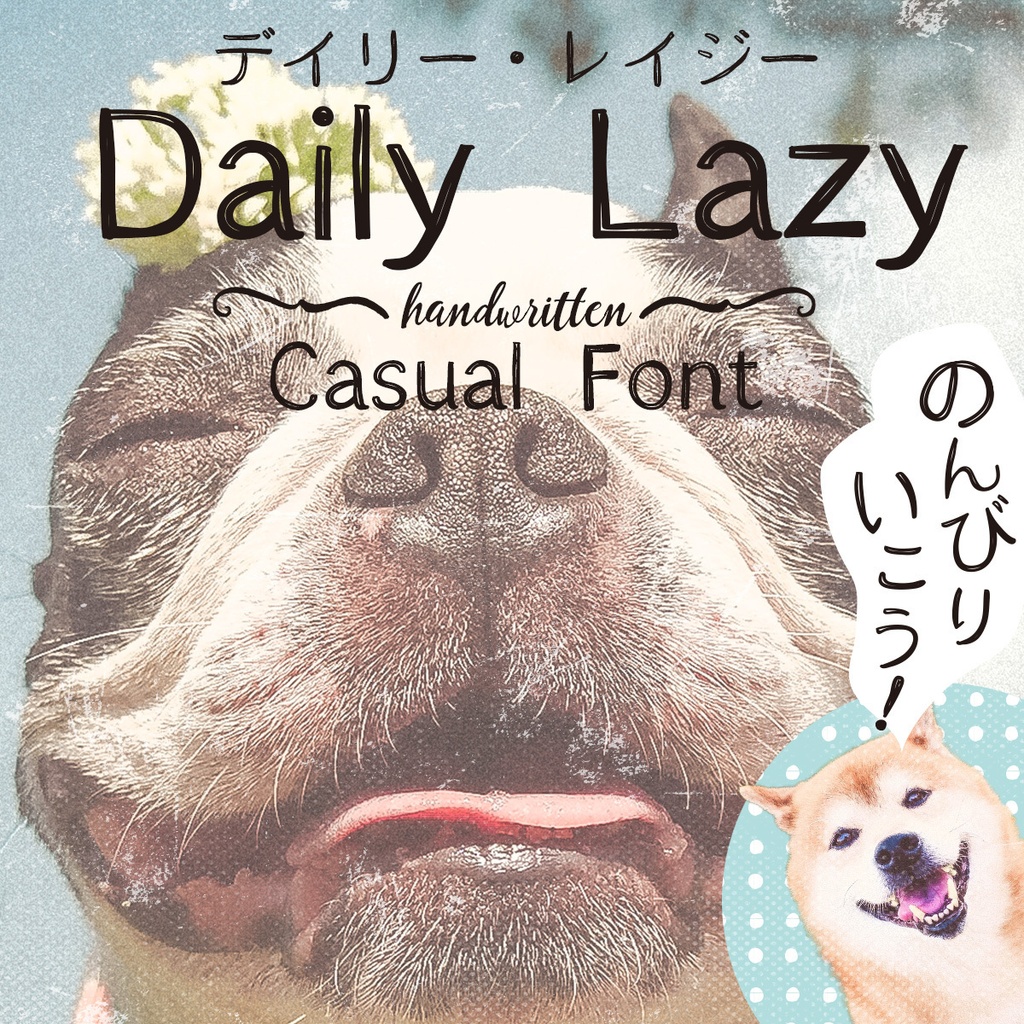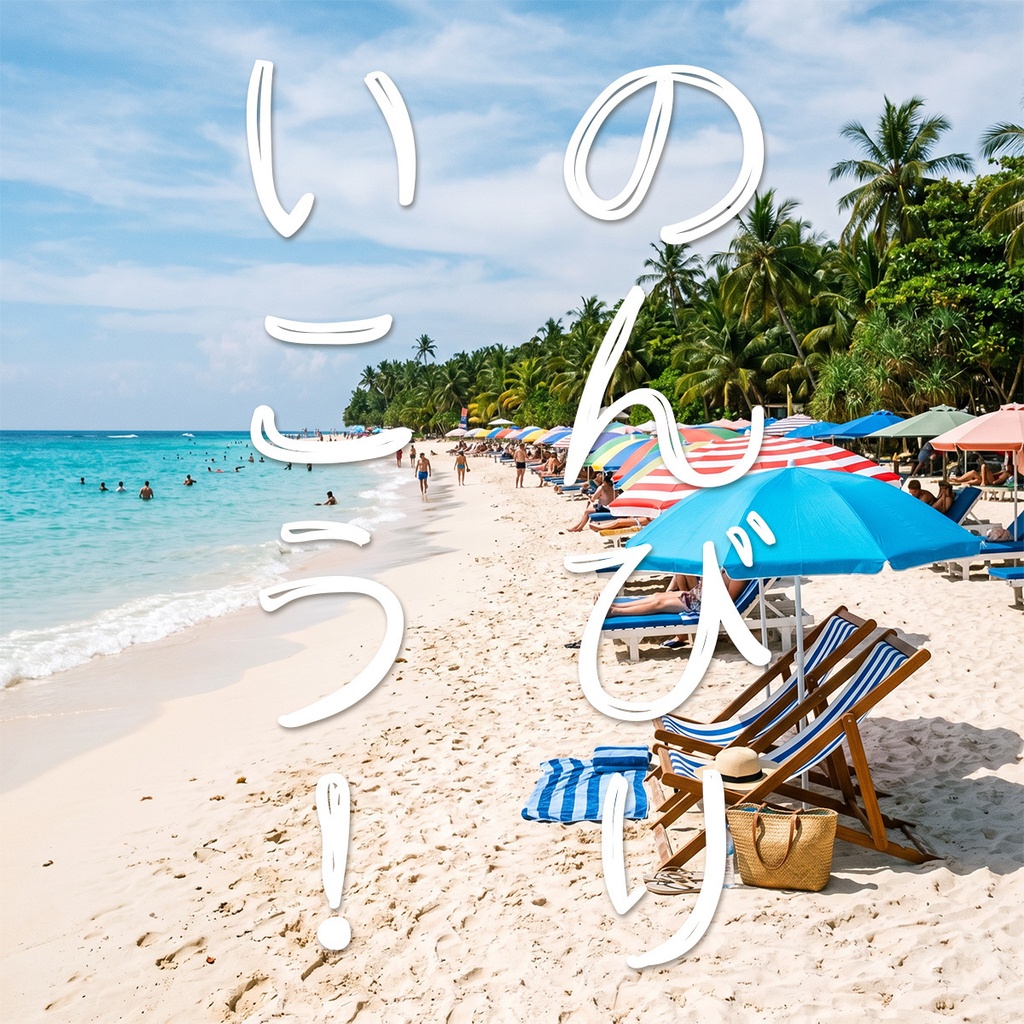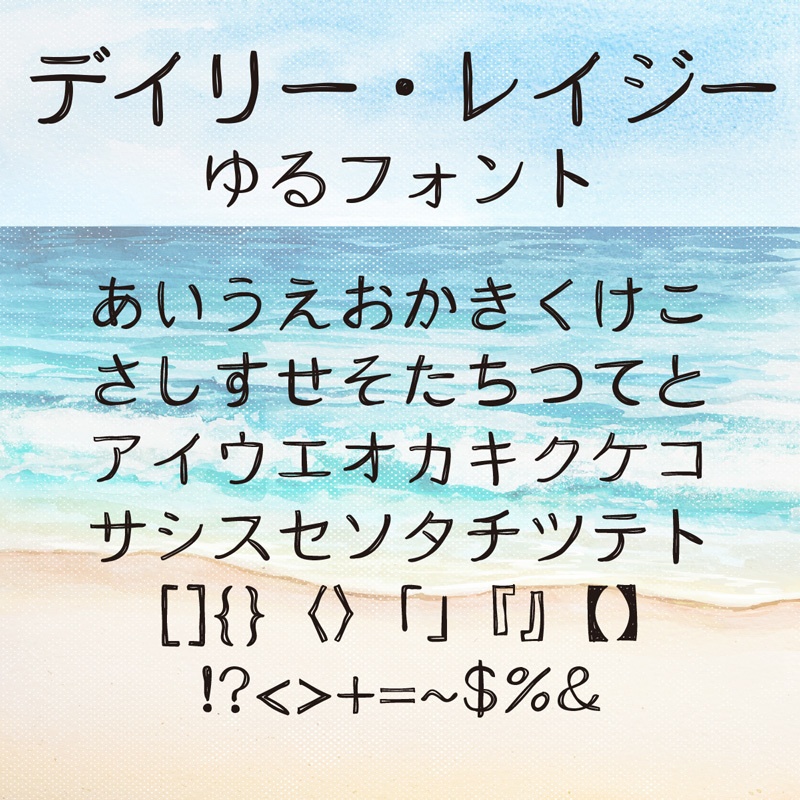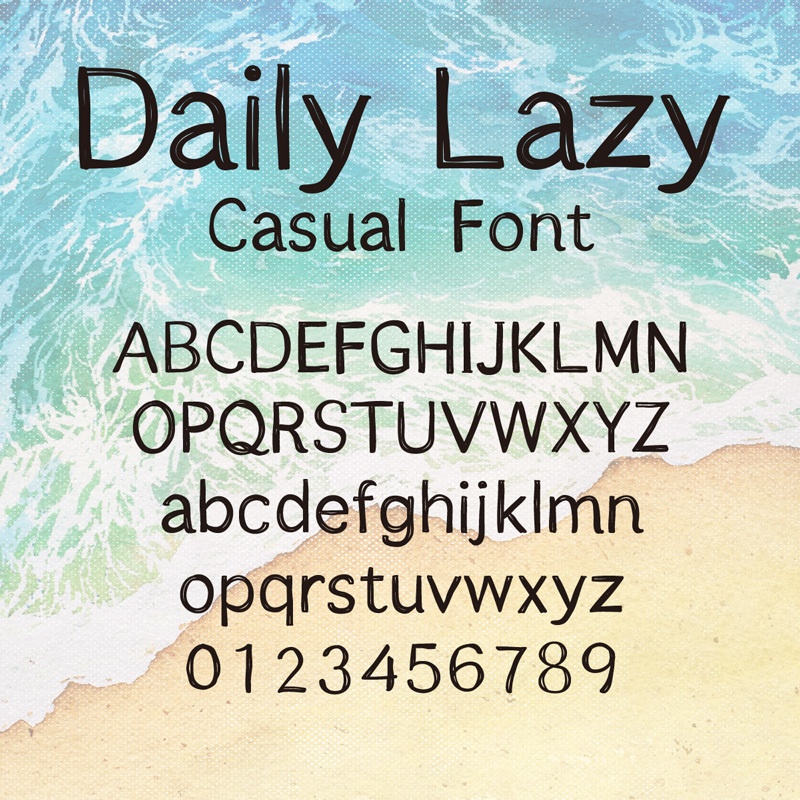
【商用可・縦書き対応】デイリー・レイジー 手書きゆるフォント ひらがな・カタカナ | Daily Lazy
デイリー・レイジー 手書き ゆるフォント
のんびりいこう! 適度なゆるさ加減が絶妙なリアル手書きフォント 【商用可・縦書き対応】ひらがな・カタカナ・アルファベット・記号を収録した、丸みのかわいい日本語フォントです。 同人誌・SNS・動画・WEBデザインなど幅広い用途にお使いいただけます。 商用利用OKです。 ひらがな・カタカナ・アルファベット・記号 収録 フォント形式:OpenTypeフォント 【動作環境】Windows / Mac 対応 【インストール方法】 Windows:ダウンロードしたZIPを解凍し、.otfファイルを右クリック→「インストール」 Mac:Font Bookにファイルをドラッグ&ドロップ ▼ まず試してみたい方へ ・無料お試し版(英数字・記号のみ)→ https://vanillabeanz.booth.pm/items/2782701